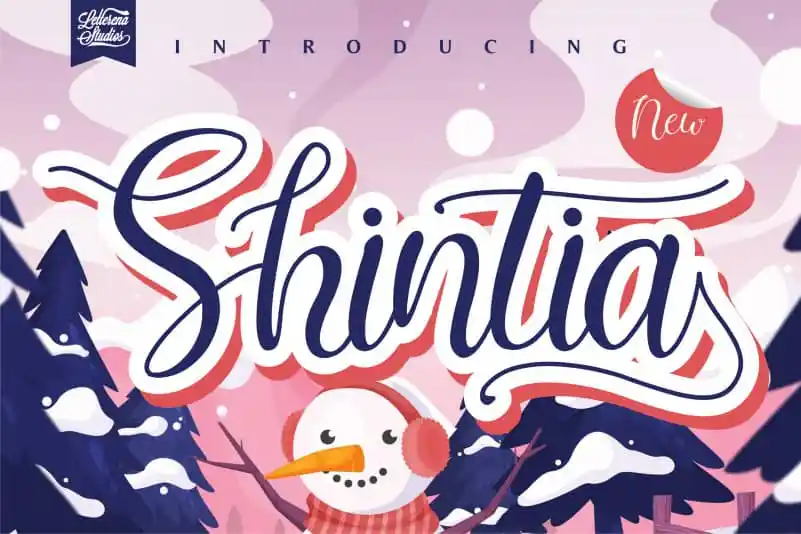
Shintia Script Font – Download Grátis
A fonte Shintia Script é uma delicada tipografia manuscrita que transmite sensibilidade e misticismo. Suas letras distintas e redondas tornam-a um verdadeiro favorito entre os designers de gráficos digitais. Ideal para cartões de aniversário, decoração de casamentos e qualquer projeto artesanal que exija um toque romântico. Este design é perfeito para celebrar o espírito natalino, assim como agradará a quem valoriza uma apresentação única e sofisticada em seus trabalhos de arte digital. Seja você criando cartões personalizados ou decorando sites com essa fonte delicada, certamente encontrarás inúmeras maneiras de explorá-la. Descubra o encanto de Shintia Script e transforme suas criações digitais em verdadeiros artigos de luxo.